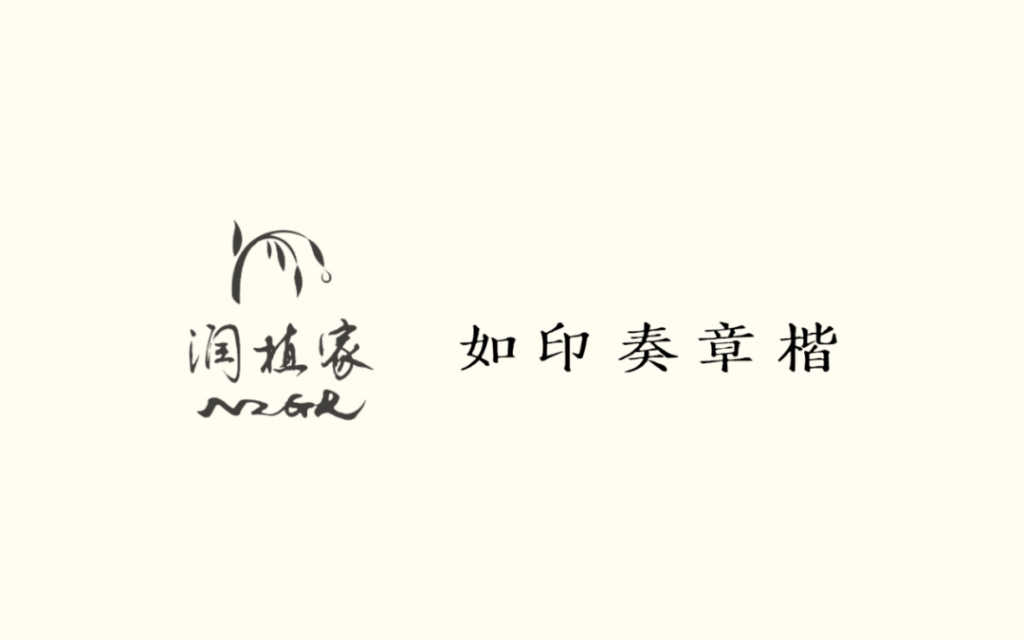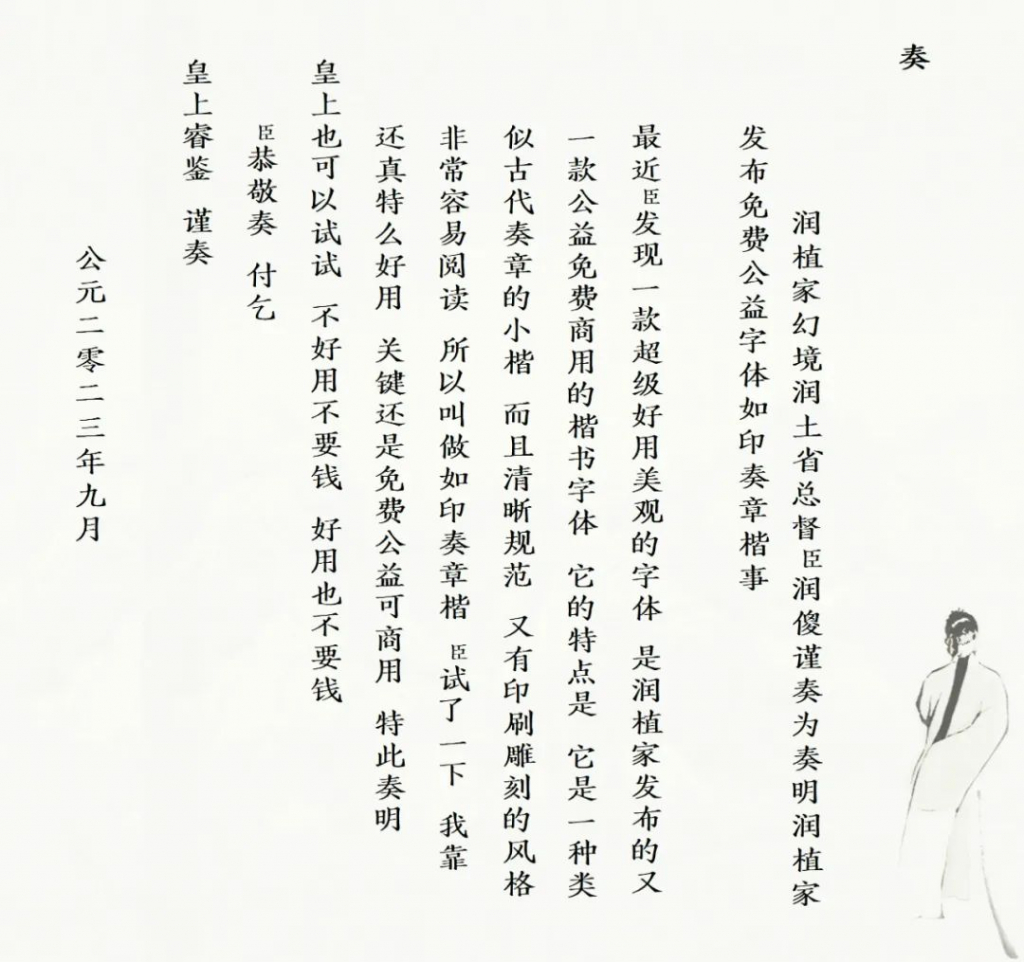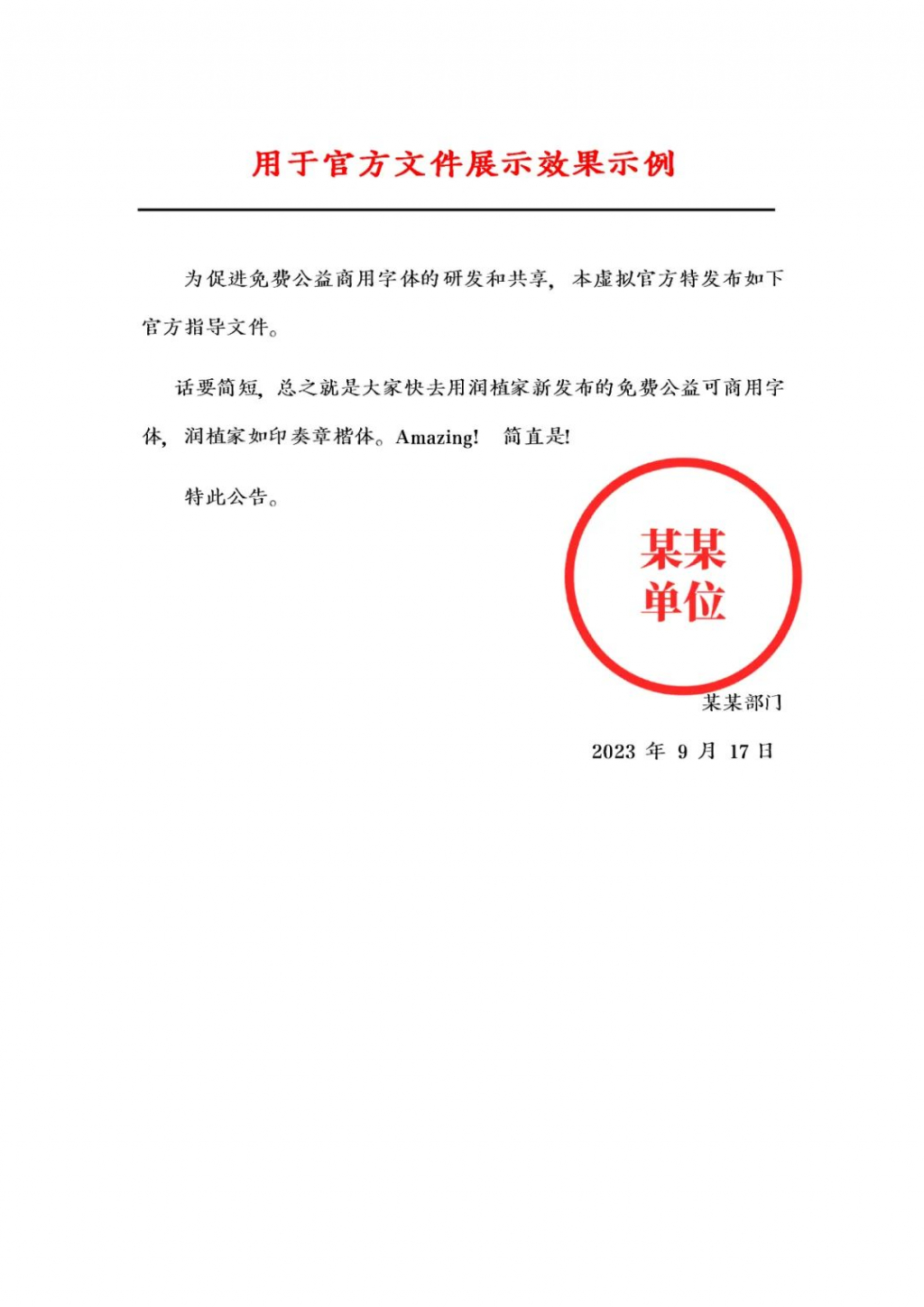
这款字体专用于大量文字,作为正文,竖排和横屏都好看,并且具有官方正式场合使用的气场,没有太大的违和感。
为什么叫如印奏章楷呢?因为这种规范中庸、有书卷气、可识别性高、适合长文阅读的字体,类似传统小楷书写的奏章,如果古代用这种字体写奏章,皇帝看了也会很舒服。
下面是模拟奏章的效果,是不是又平和工整、又养眼适合阅读?
同时,不光是直排的古代文字,横排也很好看,适合用于一些官方文件的展示哦,下面是用于官方文件展示的效果示例:
“润植家如印奏章楷”是一款书写很新颖的字体,字体大方,适合各种设计作品使用!欢迎下载!